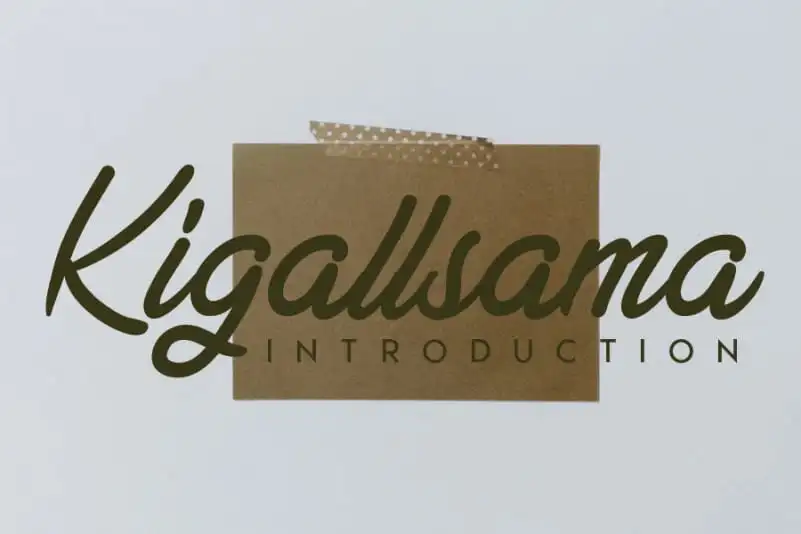
Kigallsama Handwritten Font – Download Grátis
A fonte Kigallsama Handwritten é uma delicada escrita a mão que transforma elegância simplesmente inegável numa única fonte. Suas linhas fluidas e detalhes sutis criam um ar de sofisticação, perfeito para qualquer aplicação visual – seja ela web, impressão ou vídeos em movimento. Kigallsama oferece uma variedade de opções que permitem personalizar seu design de acordo com suas necessidades específicas. A elegância da fonte é ainda mais evidente quando usada em projetos visuais. Ela não apenas enriquece a aparência visual dos seus documentos, mas também transmite um tom casual e acolhedor, tornando-a ideal para aplicativos como identidade de marca ou criação de designs gráficos pessoais. Kigallsama é uma fonte perfeita para quem busca transmitir elegância através da escrita a mão, em qualquer formato visual que escolha usar.